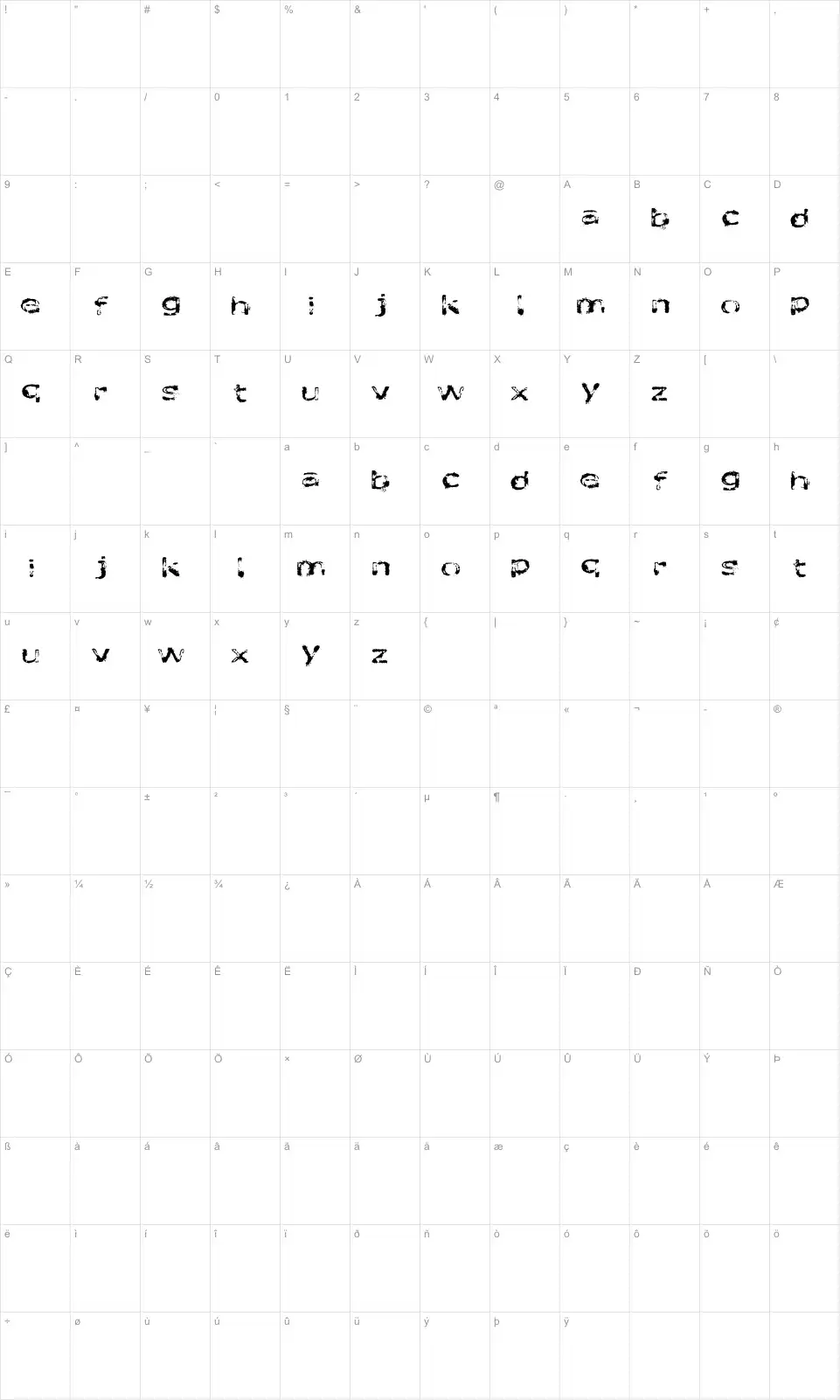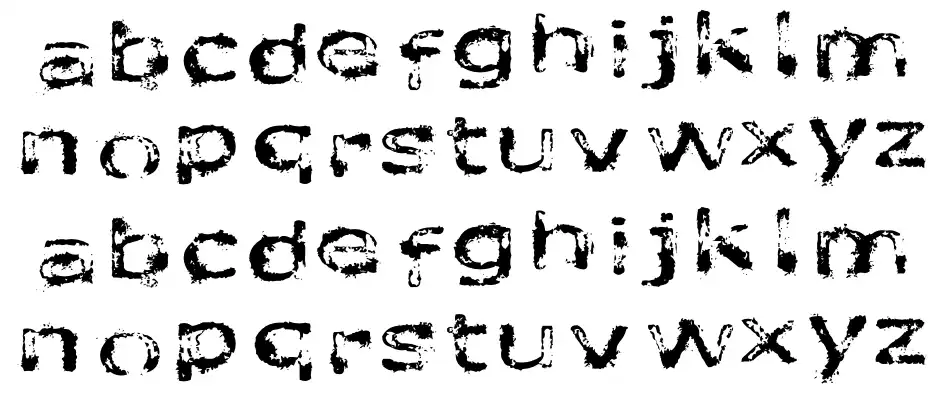
Like fonts in the rain
A fonte ‘Like fonts in the rain’ criada pelo designer Andreas Johansson é uma escolha perfeita para aqueles que buscam algo especial e extravagante para seus projetos. Este Fancy tipo de font, adicionado em 12 de julho de 2022, oferece um estilo único que certamente dará um toque único a qualquer projeto. Se você está procurando por essa font, pode baixá-la ou gerar um preview personalizado de texto para ver como ela ficará antes de usá-la. Com um tamanho de 21 KB, é leve e compacto, tornando-a fácil de usar em qualquer dispositivo. A fonte é gratuita e vem em formato TTF, permitindo que você a personalize e use de diversas maneiras. Com 1755 downloads até o momento, é evidente que ela está ganhando popularidade entre designers. Teste agora e descubra por si mesmo como ela pode personalizar seu design.
Designer: Andreas Johansson